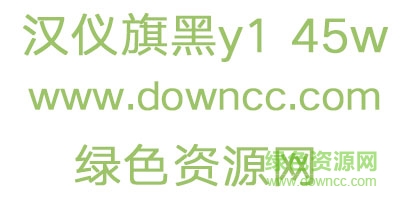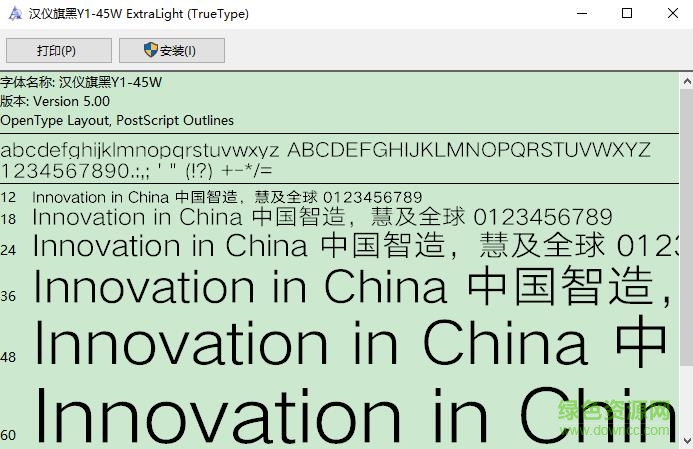
漢儀旗黑y1 45w是一款非常實(shí)用的漢儀字體,這款字體結(jié)構(gòu)工整清晰,字型樸素莊重,整體效果非常出眾,喜歡的朋友可以來(lái)綠色資源網(wǎng)下載使用!
字體家族:漢儀旗黑Y1-45W
字體風(fēng)格:Extra Light
字體版本:Version 5.00
書(shū)體類(lèi)型:黑體
字符數(shù):10253
字形數(shù):10509
漢儀旗黑是由三個(gè)系列字體(長(zhǎng)、方、扁)組成的一個(gè)龐大而完整的家族字體,從最細(xì)的25到最粗的105,共計(jì)15個(gè)字重,是迄今為止國(guó)內(nèi)最大、最豐富的字重的家族字體,可以滿(mǎn)足企業(yè)多渠道,全方位的內(nèi)容設(shè)計(jì)以及定制化需求,實(shí)現(xiàn)企業(yè)品牌形象在各渠道的統(tǒng)一呈現(xiàn)